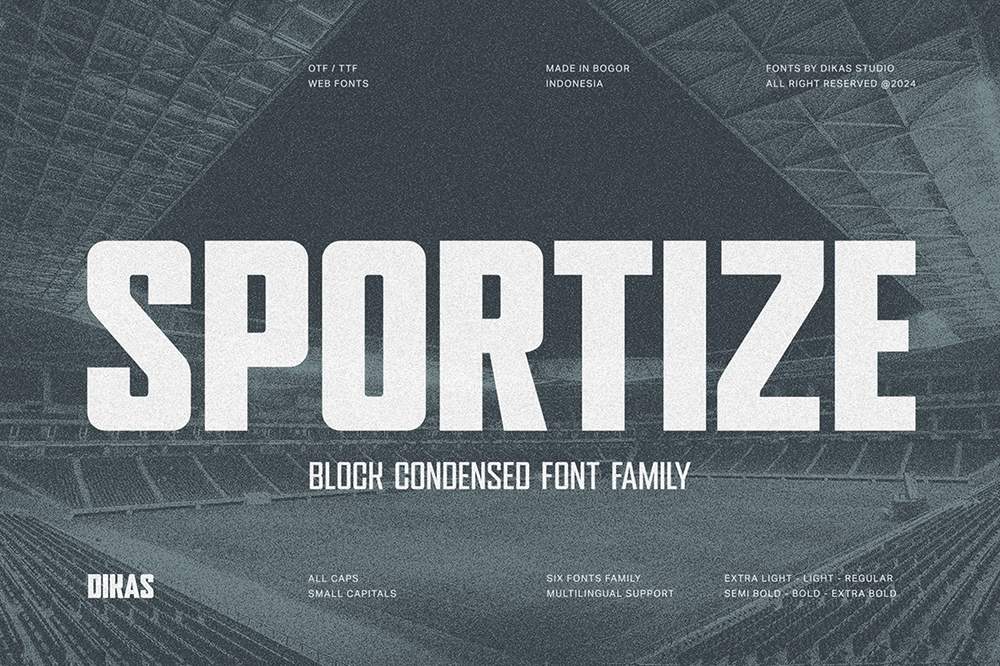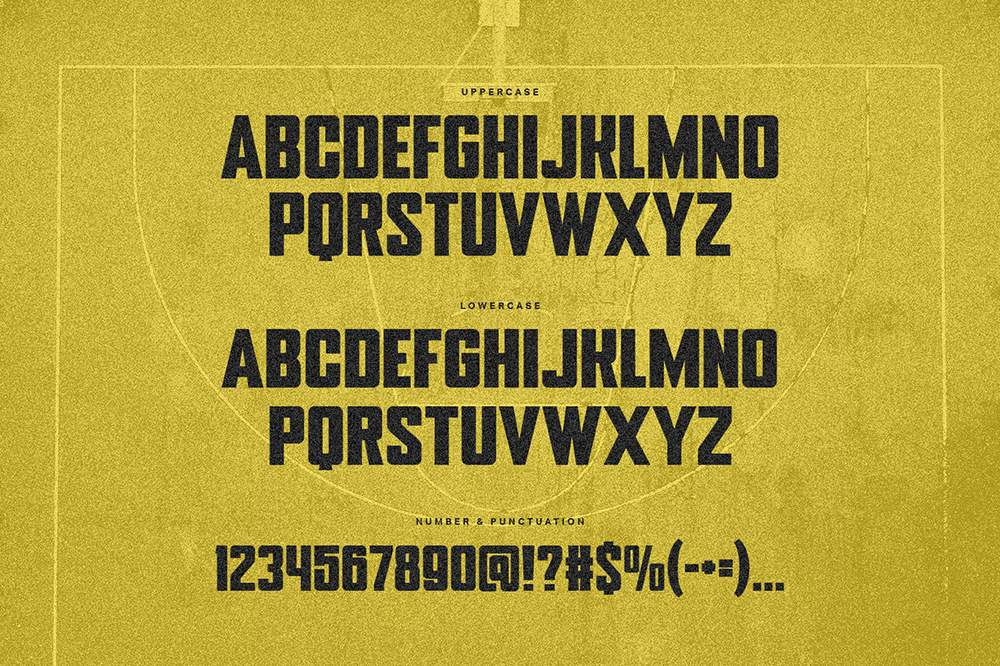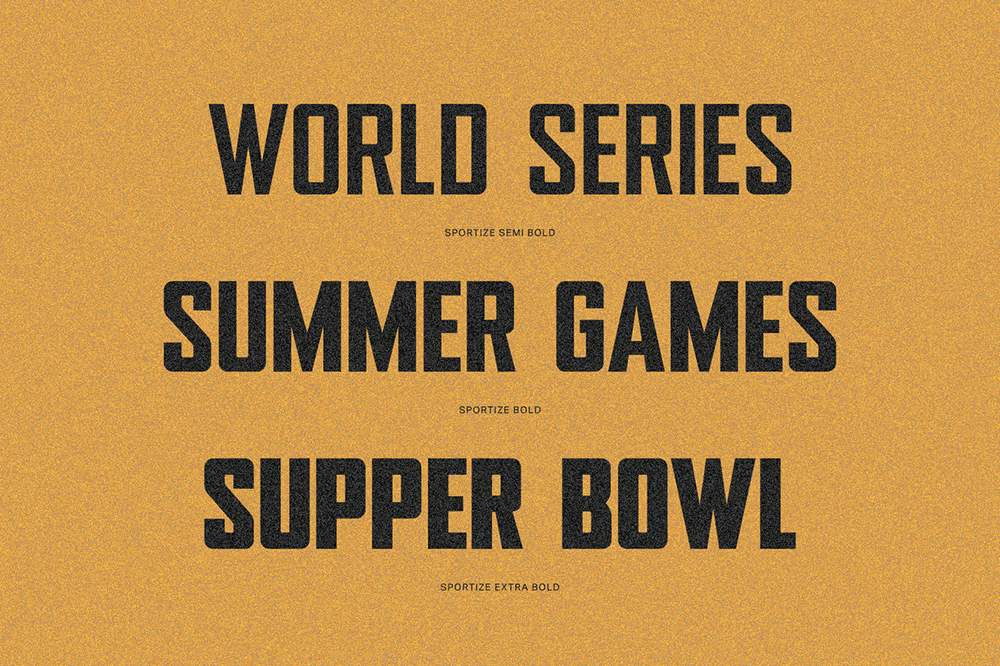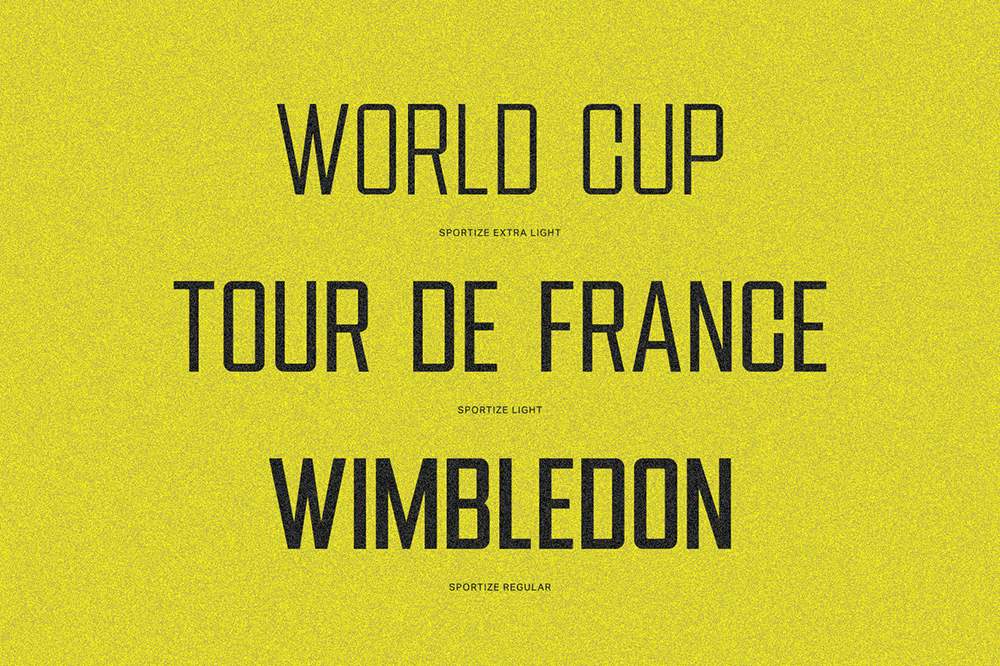
فونت پرمیوم و انگلیسی Sportize Font يک فونت سنس سریف قدرتمند و فشرده با طراحی مربعی است که برای پروژهها ايدهآل است. اين فونت در شش سبک…
فونت پرمیوم و انگلیسی Sportize Font يک فونت سنس سریف قدرتمند و فشرده با طراحی مربعی است که برای پروژهها ايدهآل است. اين فونت در شش سبک (خيلی روشن، روشن، معمولی، نيمه پررنگ، پررنگ و خيلی پررنگ) موجود است و برای تيترها، پوسترها و موارد ديگر تطبيقپذيری ارائه میدهد چه برای يک رويداد يا برند طراحی کنيد نتايج حرفهای و تأثيرگذاری را ارائه میدهد.
مزایای استفاده از فونت لاتین Sportize چیست؟